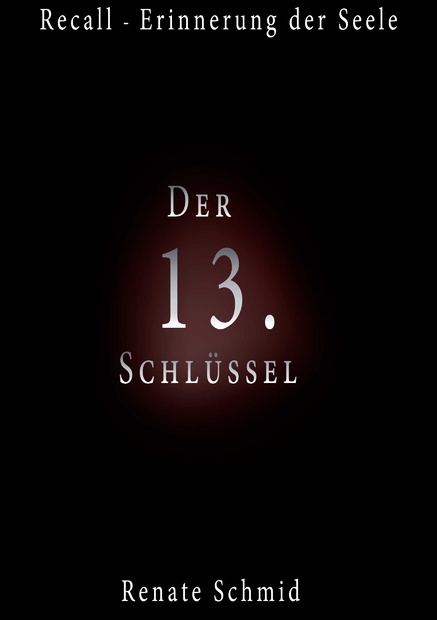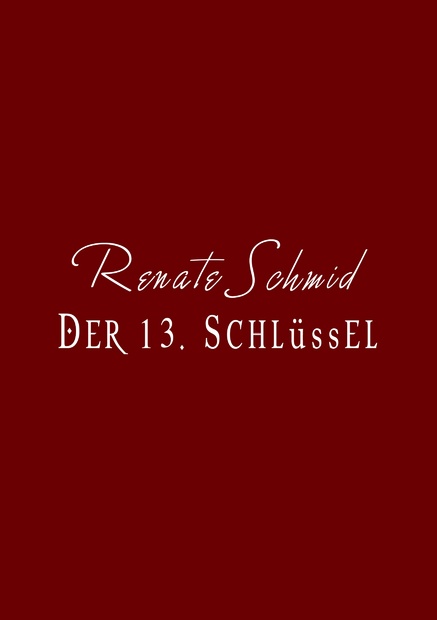
schrift für Buchcover gesucht
die Schrift im Buch soll warnock pro sein und dafür suchen wir noch eine Überschrift die dazu passt, habt ihr eine Idee für mich
Und dann suche ich noch zwei Schriften, eine für die Autorin und einen für den Buchtitel: Der 13. Schlüssel. Das Buch handelt von spirituellen Weisheiten.
Nachtrag: Ich habe mal einen Test gemacht und Frage mich, ob die Typografi so OK ist, oder ob ich es anders gestalten sollte? Die Schrift ist Garamond, oder habt ihr eine bessere Idee und welche Schrift passt zu einem Untertitel und für die Autorin?
Ich habe leider gerade nicht viel Zeit, daher nur auf die Schnelle ein paar Dinge, die mir spontan beim Betrachten Deines linken Entwurfes auffallen:
- Warum ist die »1« so groß?
- Der Abstand zwischen der 1 und der 3 ist viiiel zu groß.
- Die Kapitälchen sind keine echten Kapitälchen, die Strichstärke der Anfangsbuchstaben stimmt nicht mit der der restlichen Buchstaben überein. Verwende stattdessen lieber eine Schrift, die über echte Kapitälchen verfügt.
- Das »S« ist in die Breite verzerrt. Das sollte man dringend vermeiden, weil durch Verzerrung der Schriftcharakter zerstört wird und – in diesem Fall – das S nicht mehr zum Rest des Wortes passt.
- Die Verläufe in der Schrift erschweren die Lesbarkeit, außerdem verlaufen sie in unterschiedlichen Richtungen und sind damit nicht logisch erklärbar.
- Die Schrift ist sehr zart auf dem dunklen Untergrund und wird im Druck vermutlich noch weiter zulaufen. Ich würde einen breiteren Schriftschnitt wählen.
Bei Deinem rechten Entwurf frage ich mich, warum einzelne Buchstaben in der Größe so hervorgehoben sind. Hat das eine tiefere Bedeutung? So, das war es fürs erste, ich werde versuchen, nachher noch mal in Ruhe auf die Schriftenauswahl einzugehen.
Nachtrag: Du solltest versuchen, Dich bei der Gestaltung auf so wenige Schriften wie möglich zu beschränken und nicht für jedes einzelne Textelement eine eigene Schrift auszuwählen. Probier mal, den kompletten Titel aus nur einer Schrift zu setzen und maximal unterschiedliche Schnitte dieser Schrift zu verwenden (also auch für den Namen der Autorin).
hi ich habe mal deine Ratschläge versucht umzusetzen. Und habe mal die Minion Schrift genommen. Wir wollen gerne eine Schrift, die klar ist und die darauf hinweist, das der Inhalt des Buches, mystische Lehren des Lebens beinhaltet.
zu: Recall - Erinnerung der Seele, das soll der Oberbegriff sein, denn es sollen zwei Bände davon geben. Renate Schmid ist die Autorin.
die Zahl 1 habe ich größer gemacht, um die Zahl 13. nicht nur auf die Zahl zu beschränken, die für die Transformation des Menschen hindeuten soll, auf sein Spirituelles Erwachen, sondern auch auf die Zahl 1, die Symbolisch für den Neuanfang stehen soll und einmal die Zahl 3, die für Vielfalt, Kreativität, eine Neue Schöpfung stehen soll. Naja so recht weiß ich nicht, wie ich das darstellen soll und mir viel nichts weiteres dazu ein;) Wir haben überlegt, die Zahl 1 evtl. in weiß und die Zahl drei in gelb oder violett zu gestalten auf dunkelbraunem Hintergrund.
Der Hintergrund und die Farben des Covers und der Schrift werden noch gestaltet. Ich wollte erstmal mich mit der Typografi auseinander setzen. Alles weitere kommt danach
… Der Hintergrund und die Farben des Covers und der Schrift werden noch gestaltet. Ich wollte erstmal mich mit der Typografi auseinander setzen. Alles weitere kommt danach
Das ist aber ein integrierter Prozess, alles einzeln betrachten und erledigen zu wollen führt in den Wald.
Deine Zahlenspielerei wird außer dir wahrscheinlich niemand verstehen. Eine Zahl ist definiert, die 13 steht nun mal zwischen der 12 und der 14 und ist weder ein 1 noch eine 3. Was soll der geneigte Betrachter denn wahrnehmen? 1? 3? 13? Versuche lieber, weniger hineinstopfen zu wollen.
Wenn du z.B. bei amazon nach Büchern aus diesem Bereich suchst, findest du schon mal einige Anregungen, auch, wie man es besser nicht machen sollte.
Drei Fragen:
a) Kennst Du mein altes Lied vom Sinn oder Unsinn der Großbuchstaben bei Kapitälchen?
b) Kennst Du den Unterschied zwischen Binde- und Gedankenstrich?
c) Warum verwendest Du eine ganz schmal laufende Schrift, wenn Du sie dann sperrst?
Ganz spontan: der Titel ist »Der 13. Schlüssel« und das muß m.E. auch genau so erkennbar bleiben. Das es für die 1 und die 3 alleine noch zusätzliche Bedeutungen gibt ist schön und gut, daß muß aber anders gekennzeichnet werden. Eine farbliche Kennzeichnung wäre zwar möglich, ist aber m.E. auch nicht günstig, weil es wiederum vom eigentlichen Titel ablenkt.
Ich würde vorschlagen die 1 und die 3 mal unabhängig vom Titel im Hintergrund wieder aufzugreifen. Sobald man sie vom Titel loslöst hat man mehr Raum für Experimente ohne die Erkennbarkeit des eigentlichen Titels zu stören.
Hmmm, wenn ich das richtig sehe, dann geht es in dem Buch doch um weltanschauliche Themen und das Ganze ist als Sachbuch angelegt, richtig? Auf mich wirken die bisherigen Entwürfe, besonders die ersten, eher wie das Cover zu einem Thriller, der in der Welt der historisch-religiösen Verschwörungstheorien im Stile Dan Browns angesiedelt ist. In meinen Augen müsste das Buch in seiner Gestaltung wesentlich seriöser und kompetenter rüberkommen als in diesen Entwürfen, wenn Ihr wollt, dass Eure Zielgruppe das Buch überhaupt findet und ernst nimmt … :-?